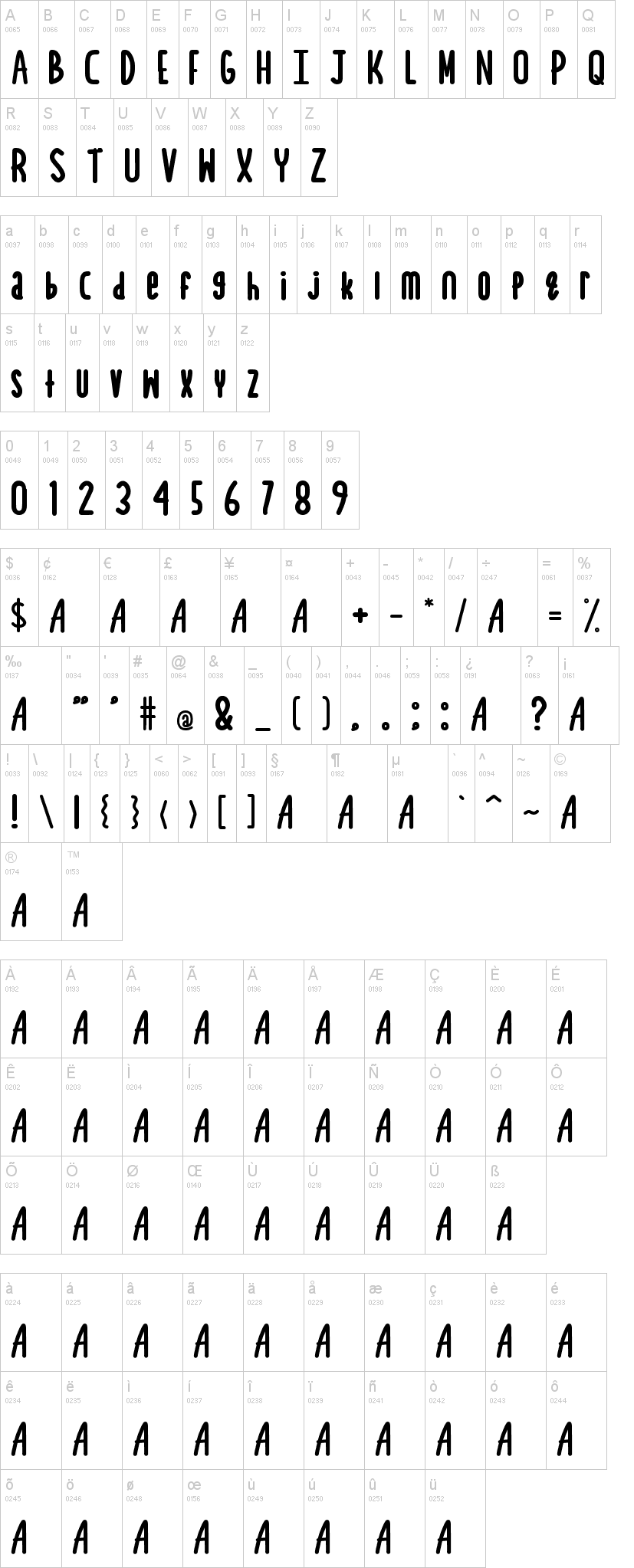
Sea Salt 是一种手写风格的字体,具有精美的笔画和轻松的氛围。这种字体具有独特的特点,它既有现代感,又有一种古老的感觉,使它成为一个非常流行的字体选择。 Sea Salt 字体由 Laura Worthington 设计,她在设计这种字体时,灵感来自于海洋和夏季的感觉,因此这种字体非常适合用于与海洋、沙滩和夏季相关的设计项目,例如海报、传单、广告、贺卡等。 Sea Salt 字体包含了大量的连字和替代字形,这些选项可以让您在设计中添加一些个性化的风格和变化。此外,Sea Salt 字体还包含了各种格式的文件,包括 TTF、OTF、WOFF 和 WOFF2,使其非常适用于各种不同的设计软件和平台。 总之,如果您正在寻找一种漂亮而富有个性的手写风格字体,那么 Sea Salt 将是一个非常出色的选择。内容介绍
Sea Salt是一款非常不错的手写艺术字体,具有很好的视觉感,适合于文化类的宣传设计、商业类品牌的广告和产品包装设计以及个性化文字排版等较多场景。